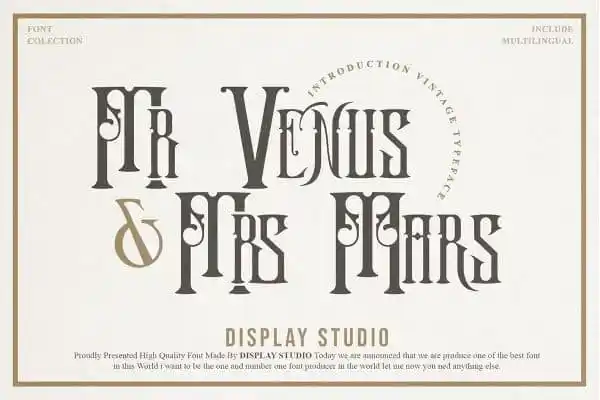
Mr.Venus & Mrs.Mars Blackletter Font – Download Grátis
Introduzimos a você a Mr.Venus & Mrs.Mars Blackletter Font, uma fonte de exibição única e intrigante criada pelo designer Display Studio. Esta fonte está perfeitamente adaptada para projetos como logotipos vintage, headlines ou embalagens. Além disso, o produto inclui um conjunto de ornamentos decorativos que permitem construir designs vintage belos em pouco tempo. Seu charme distintivo e seu design elegante fazem dele uma escolha ótima para criar trabalhos com um toque nostálgico. Este fonte é perfeito para qualquer projeto onde você deseja dar ao seu design aquele sabor retro, sem esforço. É a fonte perfeita para quem está buscando algo que seja tanto original quanto versátil. Com Mr.Venus & Mrs.Mars Blackletter Font, o trabalho de logotipo ou embalagem vintage pode ser rapidamente e eficientemente realizado.